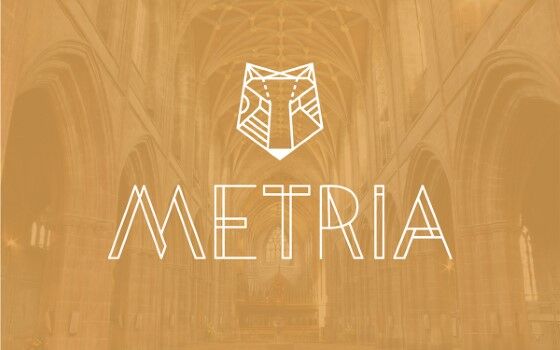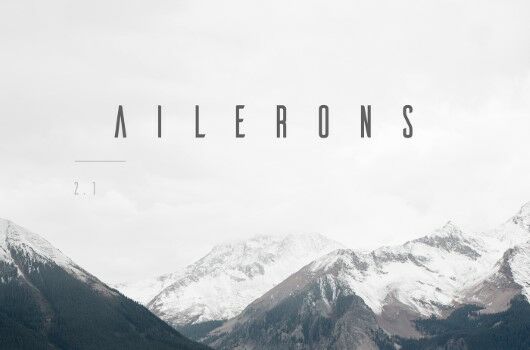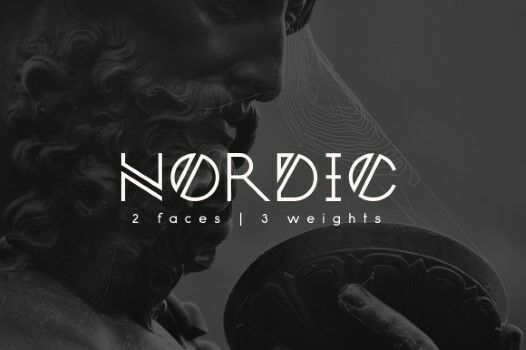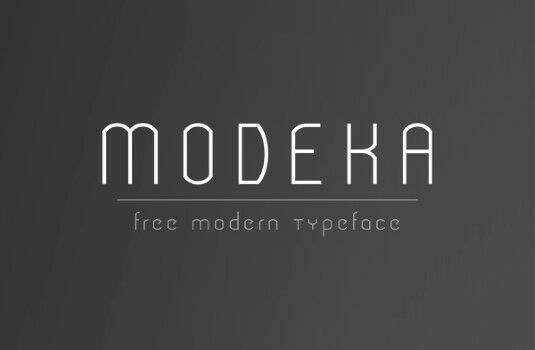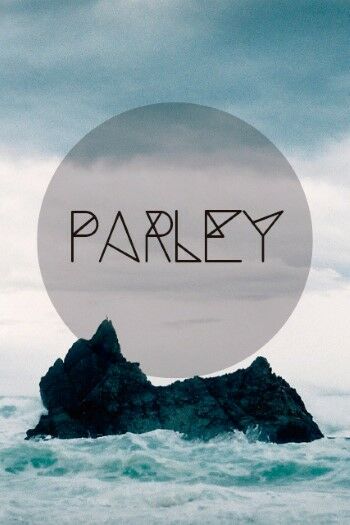
Kamu sedang mencari font keren atau font aesthetic untuk digunakan di media sosial? Bingung memilih yang terbaik? Tenang saja, kamu bisa menemukan beragam pilihan gaya tulisan menarik di artikel ini.
Saat ini memang sudah banyak website download font gratis yang menawarkan ribuan jenis font berbeda. Kamu bisa pilih sendiri sesuai seleramu.
Tapi, ada beberapa hal yang perlu diperhatikan sebelum memilih font. Selain eye-catching, tentunya sebuah font harus mudah dibaca oleh orang lain.
Nah, supaya kamu punya banyak referensi font huruf keren, langsung saja cek kumpulan nama font aesthetic untuk desain grafis yang akan Jaka berikan di bawah ini.
1. Ailerons
Ailerons adalah font dari Adilson Gonzales yang terinspirasi dari model pesawat terbang pada 1940-an. Ujung setiap huruf dibuat miring dan sedikit melengkung dengan detail yang halus. Cocok digunakan untuk judul, nih.
2. One Day
One Day adalah font ramping dan huruf besar (uppercase) dari Nawras Khrais. Bentuk font yang membulat dan garis putus-putus di bagian tertentu mampu menambah daya tarik visual tersendiri.
3. Cooper Hewitt
Ketika Museum Desain Cooper Hewitt Smithsonian diperbaiki, pihak pengelola juga melibatkan type designer Chester Jenkins untuk menciptakan font Sans Serif Kontemporer yang bisa digunakan oleh umum. Hasilnya juga keren, lho.
4. Aqua Grotesque
Font dari Laura Pol ini memiliki garis lurus yang kontras dengan bentuk yang membulat. Garis yang tegas mendominasi huruf besar, sementara bulatan halus mendominasi huruf kecil.
5. Lombok
Gaya yang paling terlihat pada font Lombok adalah serif, yaitu tidak ada garis proyeksi atau melengkung di bagian ujung huruf. Menarik banget, kan?
Font dari Alexandre Pietra ini sangat tipis dengan bentuk yang terbelah menjadi dua garis, sehingga menambah kesan unik tersendiri.
6. Modeka
Modeka dari Gatis Vilaks adalah font yang modern sekaligus elegan. Jenis tipografi ini menggabungkan garis tegas dengan garis melengkung, khususnya di bagian sudut.
Selain tersedia huruf dan angka, Modeka juga menghadirkan tanda baca dengan bentuk yang khas. Kamu bisa membuat narasi yang lebih hidup dengan font ini.
7. Nordic
Nordik adalah tipe huruf yang didesain oleh Yana Bereziner. Font ini terinspirasi oleh Norwegian runes yang berasal dari Jerman dan digunakan pada tahun 400 hingga 1800.
Font Nordic juga terbilang lengkap karena memiliki dua gaya dan tiga ketebalan berbeda yang bisa kamu gunakan. Font ini terlihat sangat cocok ketika digunakan dalam ukuran yang sangat besar.
Font-Font Aesthetic dan Keren Lainnya...
8. Parley
Parley ciptaan Filipe Rolim memiliki garis diagonal yang memotong setiap huruf dan angka. Beberapa potongan tersebut adalah bagian dari huruf, sementara lainnya adalah detail tambahan yang menambah kesan unik.
9. Boxing
Sesuai namanya, font Boxing karya Tano Veron terinspirasi oleh poster pertandingan tinju bergaya retro. Tipografi ini hadir dalam style normal dan bergaris. Jika kamu suka tipe huruf tegas, tebal, dan merapat, maka font ini cocok untuk kamu.
10. Metria
Metria adalah jenis huruf geometris yang memiliki sudut konsisten dan lingkaran yang tidak sempurna. Font ini juga bakal cocok untuk berbagai jenis desain.
Desainer Jake Lunde mengungkapkan bahwa font ini terinspirasi dari bentuk geometris yang kaku dan digabungkan dengan garis lengkung yang membuatnya menjadi lebih hidup.
11. Arenq
Aesthetic fonts DaFont bernama Arenq adalah font dari Paulo R. Font ini memiliki ciri khas garis-garis yang membentuk masing-masing huruf.
Gaya tersebut menghasilkan kesan retro dan futuristik. Ditambah dengan efek gradien pada setiap karakternya, dijamin semakin estetik.
12. Fontaine
Fontaine adalah jenis huruf yang terinspirasi oleh gaya Art Deco, cerita detektif, serta berita dan iklan vintage. Font ini terlihat sangat cocok untuk judul poster film karena jelas, mudah dibaca, dan memiliki sedikit nuansa drama.
22. Attention
Sesuai namanya, font Attention bakal bisa menarik perhatian siapa saja yang melihatnya. Sebab, font ini memiliki style handwriting yang terlihat estetik dan bakal cocok untuk berbagai kebutuhan.